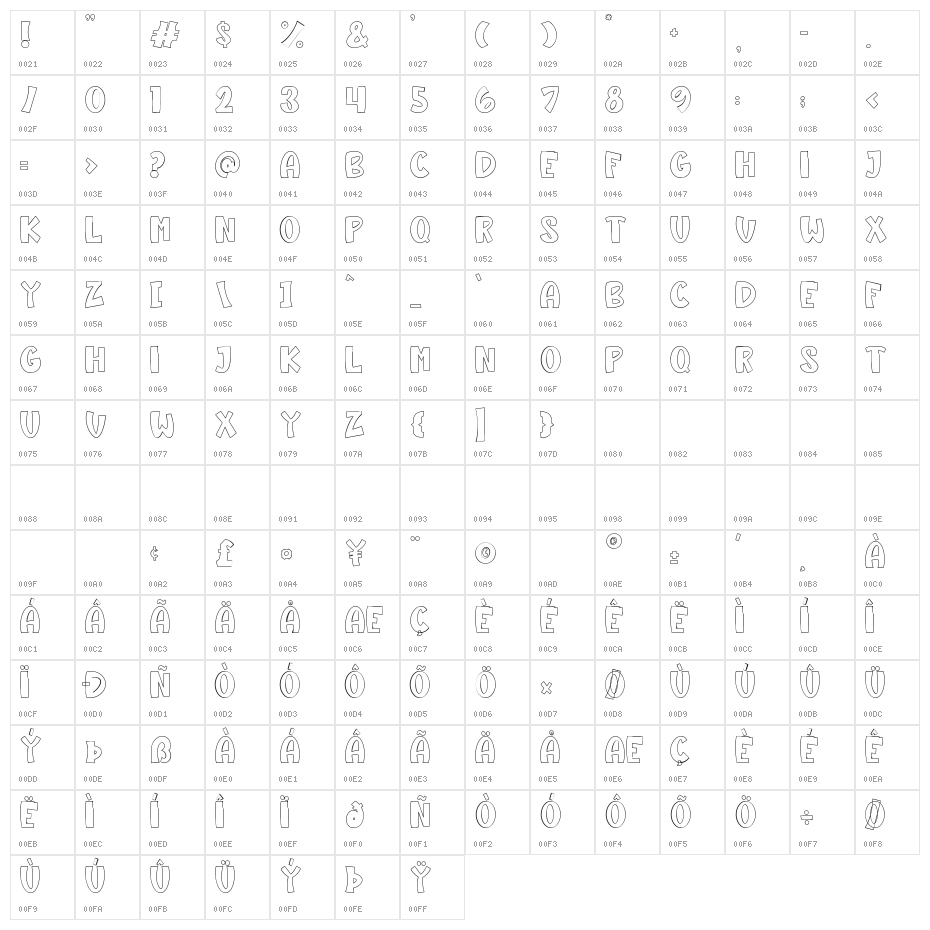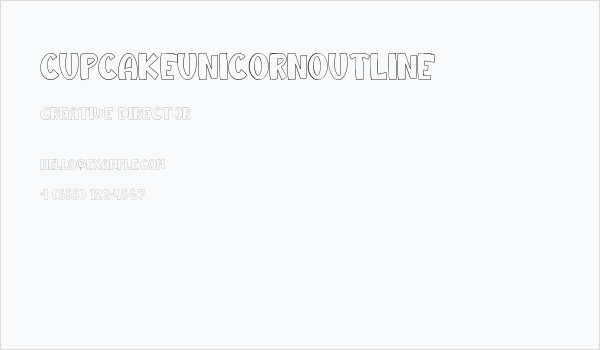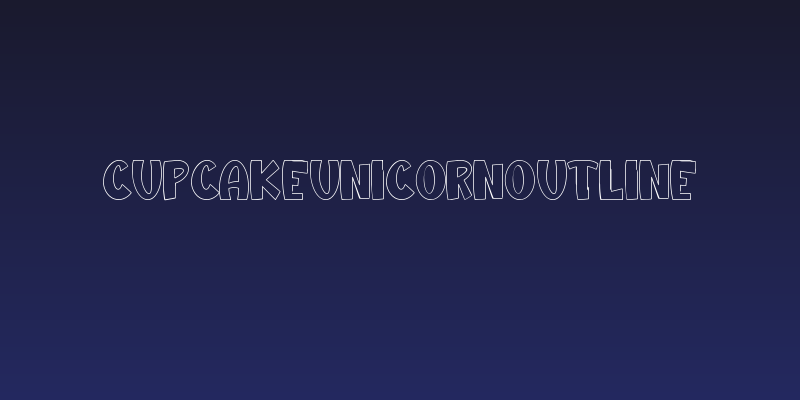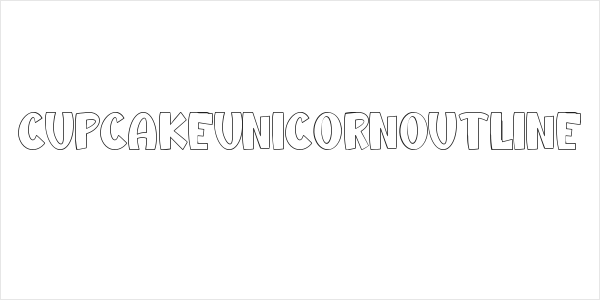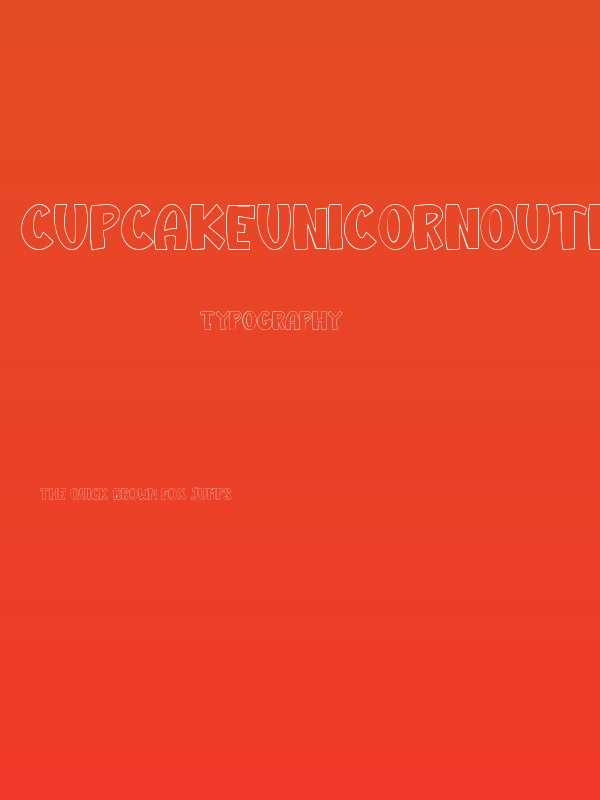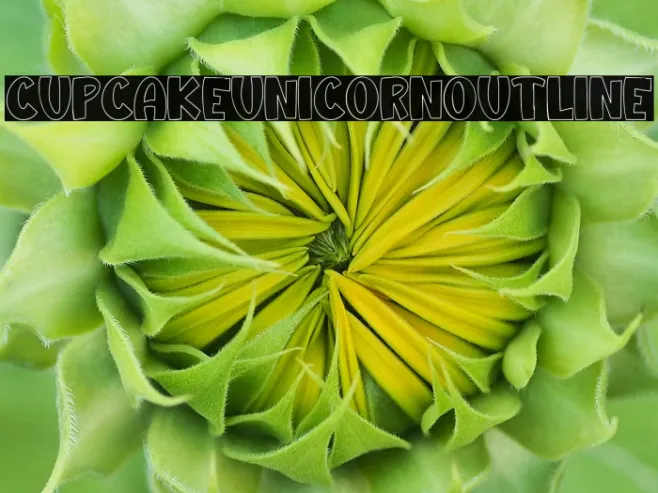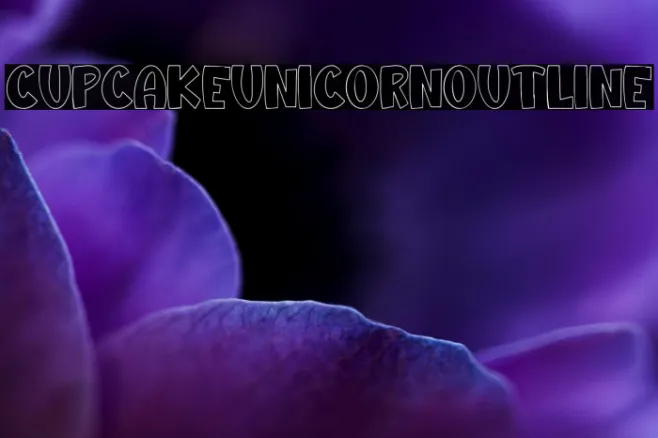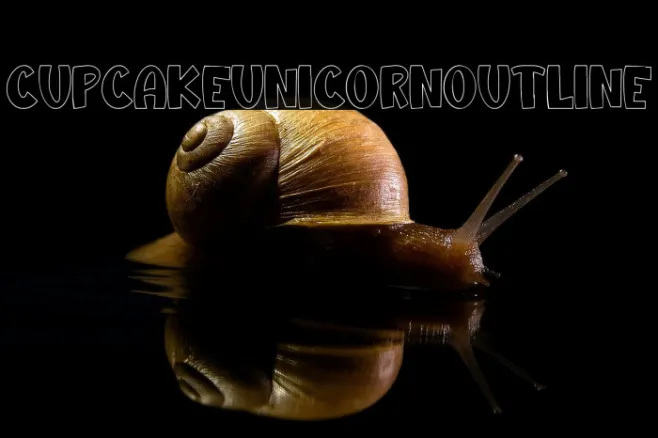
CupcakeUnicornOutline Font
| Schriften Familie | Cupcake Unicorn Outline |
| Gesamtstil | Playful, Whimsical |
| Anwendungsfall | Headlines, Logos, Creative projects |
| Vorgeschlagene Projekte | Ideal for children's books, party invitations, playful branding, and DIY projects. |